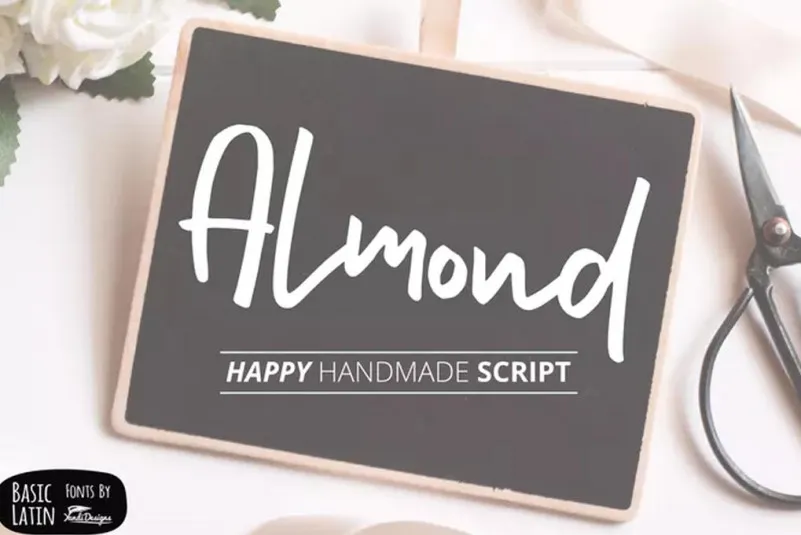
Almond Hand Lettering Script Fonts – Download Grátis
Sinta-se à vontade para adicionar uma fonte chamada “Almond Hand Lettering Script Fonts” ao seu projeto quando busque por uma escrita artística e elegante, que combina modernidade com graça natural. Esta fonte é perfeita tanto para projetos de texto quanto para assinaturas, logotipos ou cabeçalhos. Com a inclusão de um arquivo TTF (formato de arquivo popular) e EOT (em formato que funciona em dispositivos móveis), sua criação será mais versátil e adaptável. O melhor é que ela inclui caracteres básicos do idioma inglês, bem como números e símbolos, garantindo uma comunicação eficaz sem preocupações. Completamos essa fonte com o Unicode Basic Latin, oferecendo um acesso amplo aos caracteres da língua inglesa e sua variação para diferentes usos de texto em projetos diversos. A designer guxjohn criou este rico conjunto de letras, trazendo uma personalidade única à cada linha. O trabalho desta fonte é perfeito para aqueles que buscam um equilíbrio entre modernidade e elegância na escrita, tornando-a ideal não só para designers de logotipos ou editoriais digitais, mas também para os profissionais de marketing e comunicação visual em busca de uma fonte única. Com a “Almond Hand Lettering Script Fonts” você consegue fazer seus projetos realmente brilhar, sem se preocupar com um estilo antigo e desatualizado. Adicione este design único à sua próxima criação gráfica e permita que a “Almond Hand Lettering Script Fonts” faça seu trabalho. Compreender o valor de uma fonte versátil pode transformar a maneira como você percebe o mundo do design, criando um ambiente de criação mais amplo e inspirador.
Designer: guxjohn